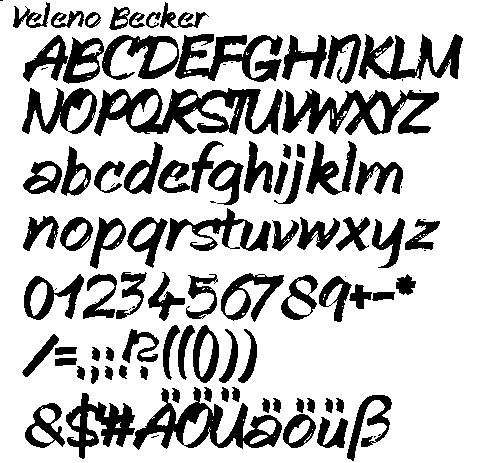
Dass man etwas kostenlos im Internet bekommt, heißt bekanntlich nicht, dass es generell »frei« wäre. Das »Becker« deutet auf eine Schrift von Data Becker hin, die wahrscheinlich Teil eines kommerziellen Fontpaketes dieses Unternehmens ist oder war.
die Databecker-Sammlung habe ich noch aus grauer Vorzeit ... Schaun wir doch mal:
Möglicherweise hat DataBecker aber diese Schrift auch nur irgendwoher heholt und kopiert? Kennt einer das Original? Ich hänge mal die Fontmap aus meinem E-Katalog an:
Kennt einer das Original?
Es gibt die Velorex von Fontana Type Foundry, die sieht wie eine verschiefte Version davon aus. Ich nehme aber mal an, dass hier die Veleno Becker das Vorbild war und nicht umgekehrt.
Da DataBecker ja vor 2 1/2 Jahren dicht gemacht hat, dürften die DB-Schriften zur Abandonware geworden sein, Allerdings bedeutet das noch lange nicht, dass sie hierdurch auch zur Freeware wurden. Zudem hab ich selbst bei DB-Schriften 1:1 Kopien kommerzieller Schriften (ohne Hinweis darauf in den Metadaten) gefunden (die waren wirklich mit den Ankerpunkten der Konturen absolut deckungsgleich, was bei neu zeichnen einer schon wo anders veröffentlichten Schrift nie passieren kann.) sodass ich über die Legalität der Schriften an sich schon im Zweifel bin.
Es gibt die Velorex von Fontana Type Foundry, die sieht wie eine verschiefte Version davon aus. Ich nehme aber mal an, dass hier die Veleno Becker das Vorbild war und nicht umgekehrt.
Angaben zur Velorex  auf der Seite: Date: 24 Feb, 2013
Und die DB-Schrift ist doch etwas älter ...
Da hast Du wohl jemanden erwischt? Jaja ...
Na ja ... eine brute force Suche über alle Pinselschriften des Typs dry brusch erscheint mir etwas aufwändig ... Myfonts hat da zwar nur 36 Schriften als Ergebnis, aber nicht die passende ... Irgendwie sehe ich da keinen systematischen Ansatz. Die Bildersuche mit Google und den Stichworten Velo oder Bicycle plus Typeface plus Brush lief auch erst mal ins Leere ... Aber vielleicht hat da doch noch jemand einen Tipp? Eine Eingebung? Eine Erleuchtung?
Wenn ich all die Infos - von denen ich nur einen Teil ganz verstehe - zusammenfasse, dann darf ich die Veleno Becker also eigentlich nicht gewerblich verwenden, wenn ich sie mir als so genannten Free Download geholt habe. Die Nutzung der Velorex wäre dagegen - wenn mit Lizenz erstanden - o.k. Sie scheint zwar eine fast kopierte Variante der Veleno Becker zu sein, aber das wäre ggf. das Problem des Variantenerstellers. Liege ich da richtig?
@ BKH-Dieter
Die 2500 Fonts umfassende Sammlung „Das große Schriftenpaket“ von Data Becker gibt es bei Amazon von mehreren Verkäufern für maximal drei Euro. Hat mal knapp 10 Euro gekostet. Und bei dem Preis ist klar, dass bei Data Becker auch nicht alles astrein war. Von wegen Raubkopien und so. Oder die Schriften sind schlichtweg alle sauschlecht. Meist ist aber in solchen Sammlungen die eine oder andere Schrift brauchbar. Jedenfalls hätte ich Data Becker gegenüber keine moralischen Bedenken, mir fsType auf Null zu setzen. Für diesen Zweck gibt es mindestens ein kostenloses Tool. Kann man aber auch mit TTX machen. (TTX ist im Adobe Font Development Kit for Opentype enthalten.) Wenn es was Offizielles ist, würde ich mir trotzdem eine andere Schrift suchen, mich informieren, ob die Lizenz die Einbettung in PDF abdeckt und die Lizenz gegebenenfalls erwerben.